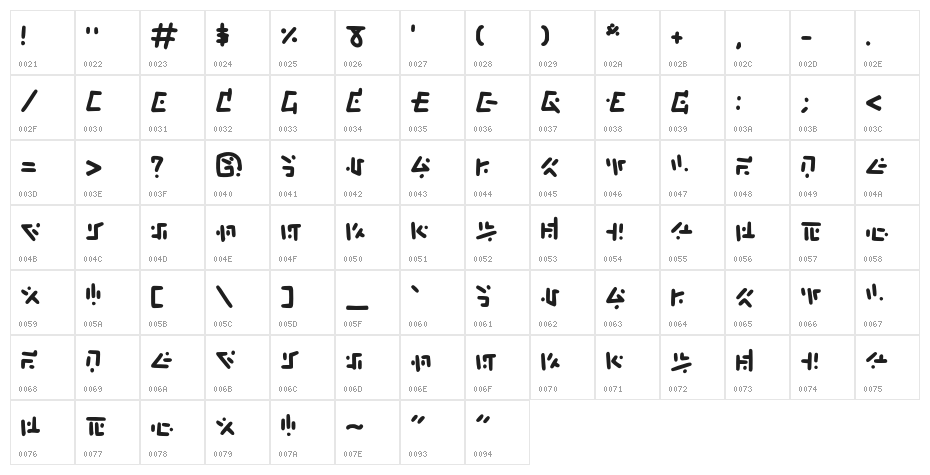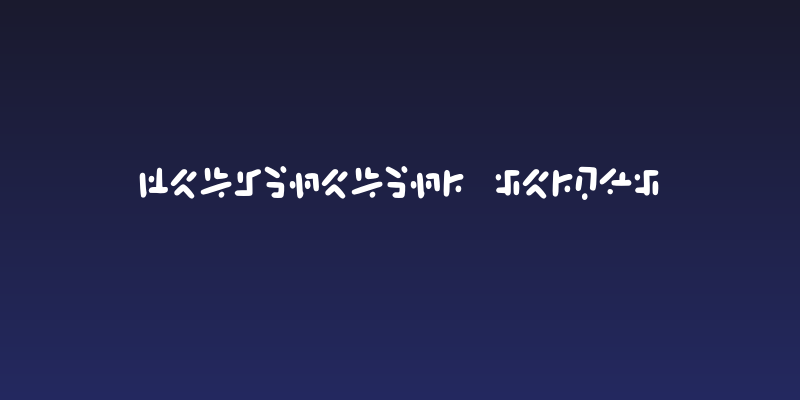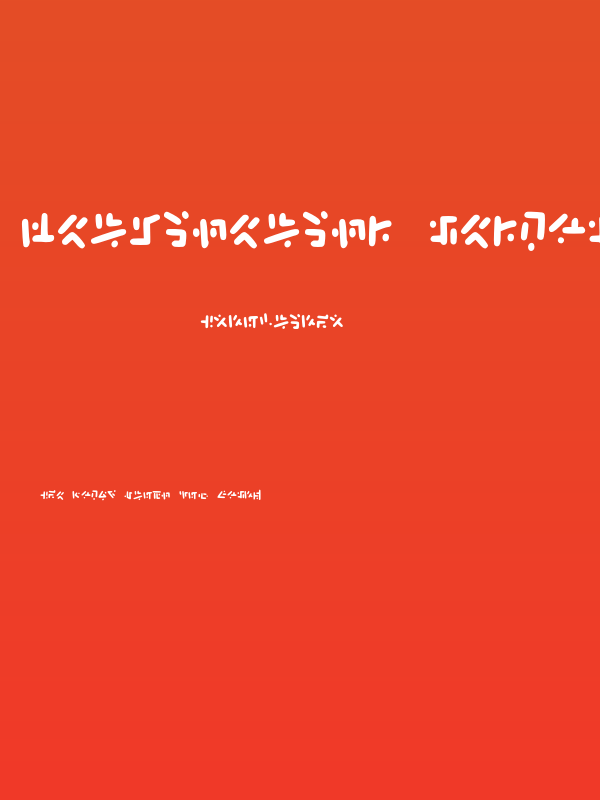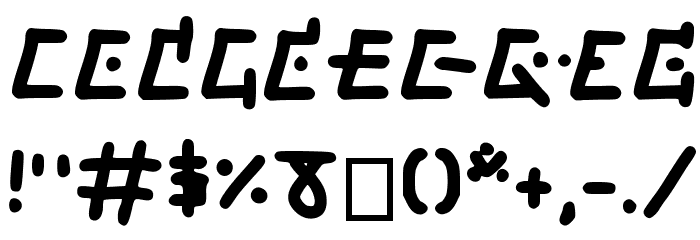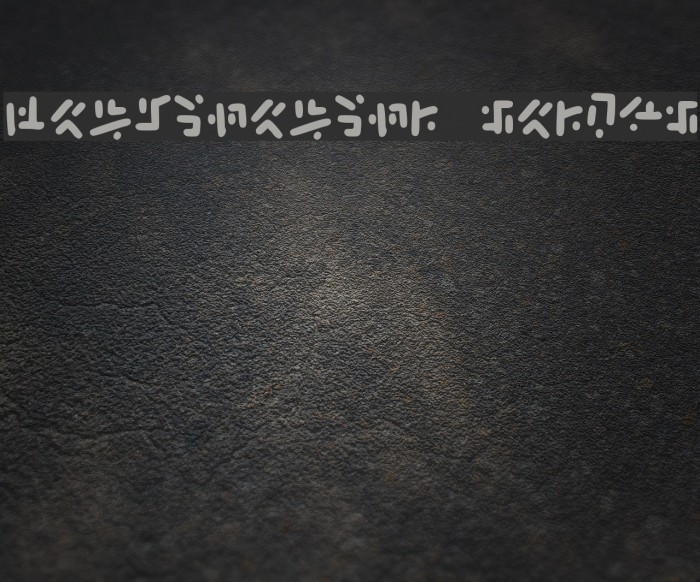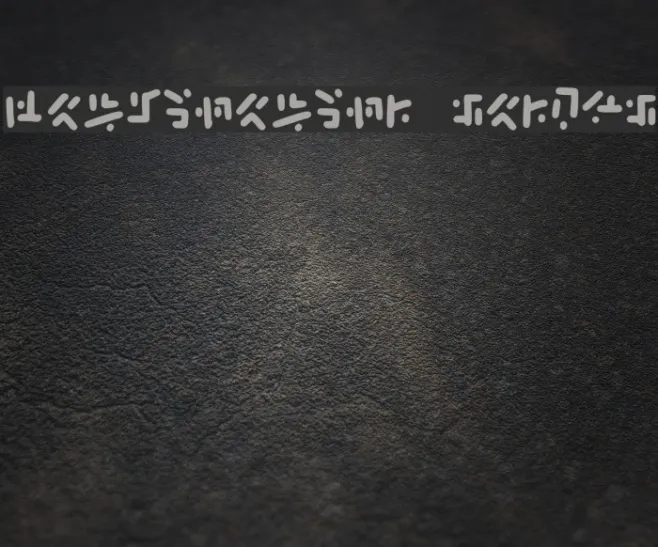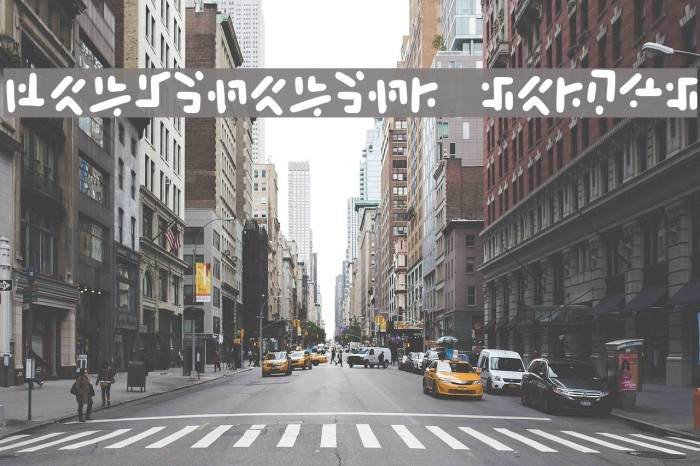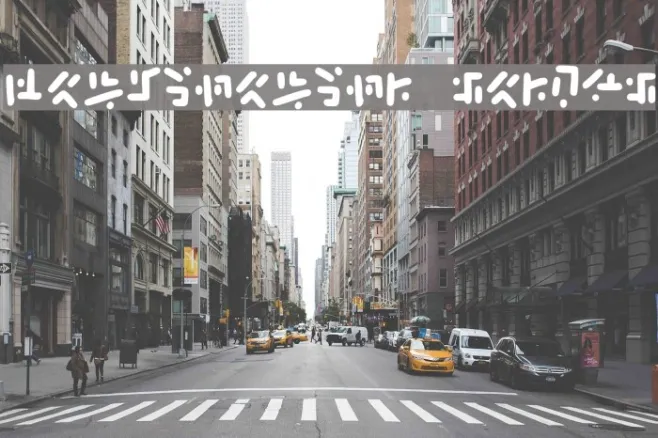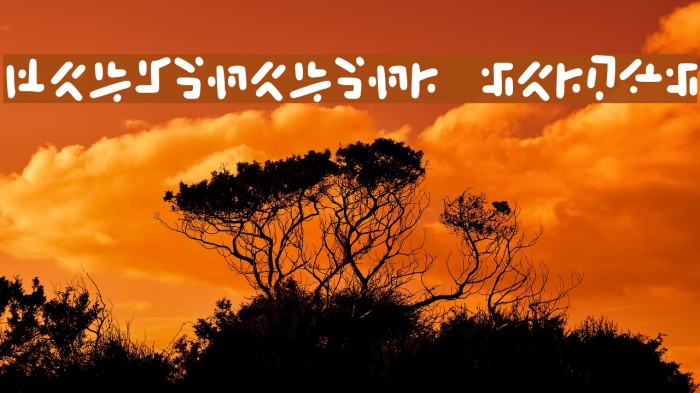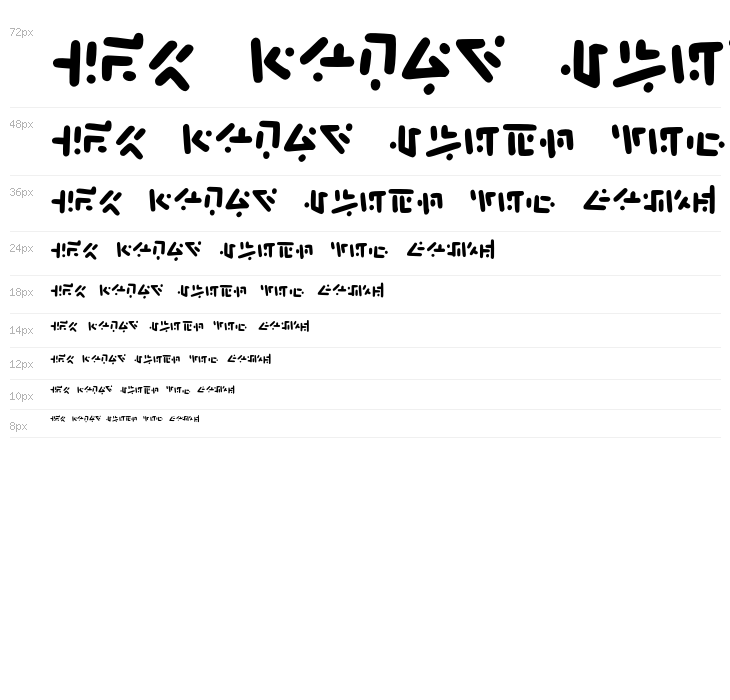
Verlanerand Medium Font
| Estilo general | Modern, Decorative |
| Caso de uso | Logos, Posters, Creative projects |
| Proyectos propuestos | Ideal for creative projects such as album covers, posters, or branding that requires a unique and striking typeface. |